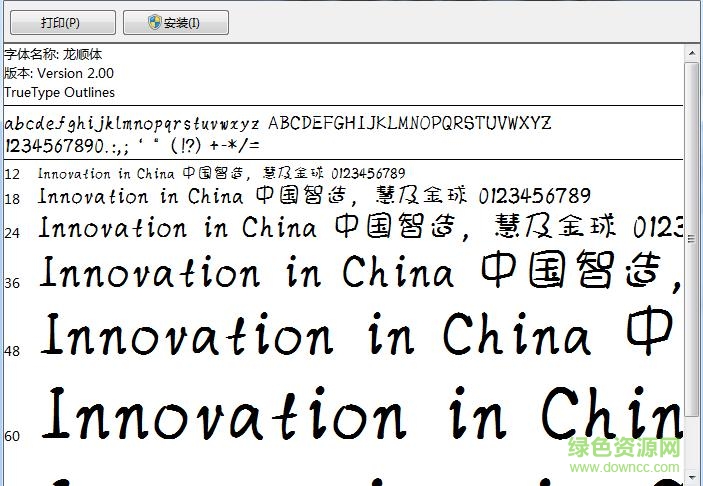
龍順體是一款非常有特色的手寫字體,字體骨骼清秀、遒勁有力,清冽而又優(yōu)雅、從容,令人賞心悅目,有喜歡的朋友歡迎下載使用!
龍順體是一款根據(jù)手寫字打造的而來的藝術(shù)字體應(yīng)用,落筆干凈爽快、字跡工整簡(jiǎn)約并且?guī)в幸稽c(diǎn)q意,適用于美工創(chuàng)作、網(wǎng)站設(shè)計(jì)、平面設(shè)計(jì)、封面設(shè)計(jì)、名片設(shè)計(jì)等方面。